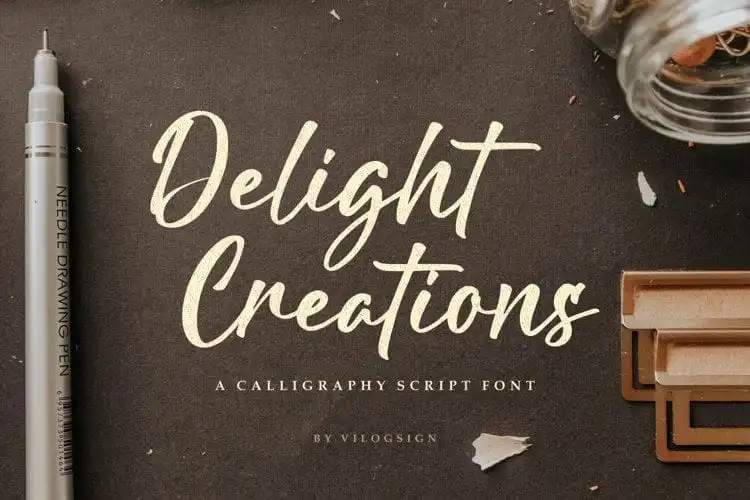
Delight Creations Script Font – Download Grátis
A Delight Creations Script Font é uma fonte escrita a mão que transmite sensibilidade e elegância com cada traço. Ela foi meticulosamente projetada por Nur Kholis para se tornar sua escolha favorita, criando um toque singular perfeito para qualquer projeto. Esta fonte é versátil e possui suporte multilíngue, permitindo-lhe completar suas necessidades de design. Ela é ideal tanto para criação de marca, camisetas, revistas, moda, citações, logotipos e embalagens. Sua beleza única a torna uma escolha ótima para qualquer projeto que deseje dar um toque pessoal e sofisticado.